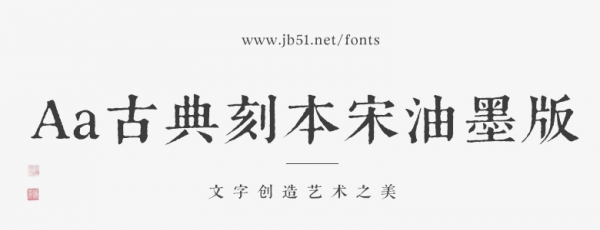
Aa古典刻本宋油墨版在原字形结构不变的前提下,通过外轮廓的不规则变化,再现元明刻本在技术有限条件下斑驳不规则的印刷效果,传递历经岁月、古色古香的视觉风貌。
Aa古典刻本宋油墨版字库是一套标准的中文字体(也称为中文字型)的字库集,字库集内包含了汉字、字母、数字、图形符号等字符组成一套完整的字库集。以供用在印刷和计算机、手机、数字媒体及相关电子产品上使用。Aa古典刻本宋油墨版字库深受广大设计师、排版师、印刷工作者、网页开发者和其他与文字相关的专业人士喜爱。Aa古典刻本宋油墨版字库中的不同字体可以传达不同的情感、风格和品牌形象,因此选择合适的字体对于视觉设计至关重要。